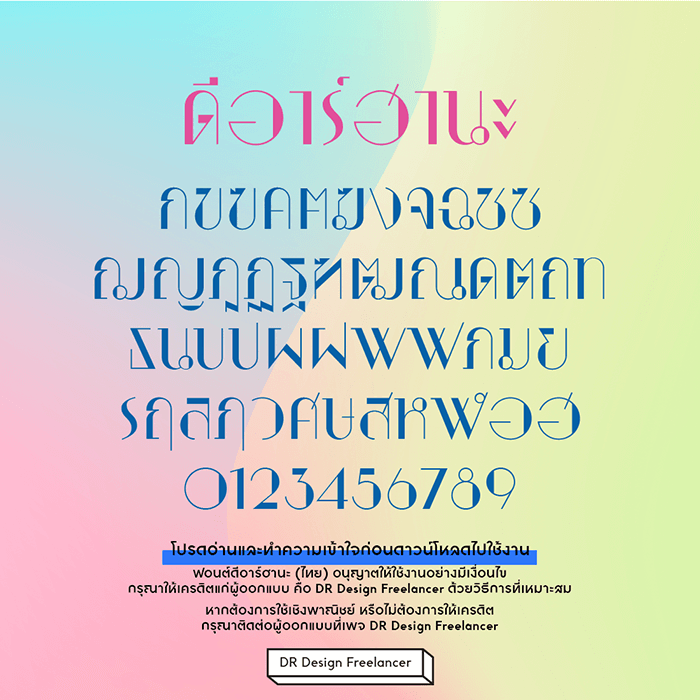
DRhana (ดีอาร์ฮานะ)
ดีอาร์ฮานะ เป็นชุดตัวอักษรเฉพาะภาษาไทย เลขอารบิค และสัญลักษณ์พื้นฐาน มีลักษณะเป็น Display Typeface ยังคงแนวคิดการออกแบบเหมือนฟอนต์อื่นๆ ของ DR Design ที่เคยฝากผลงานไว้ คือ ความสุข